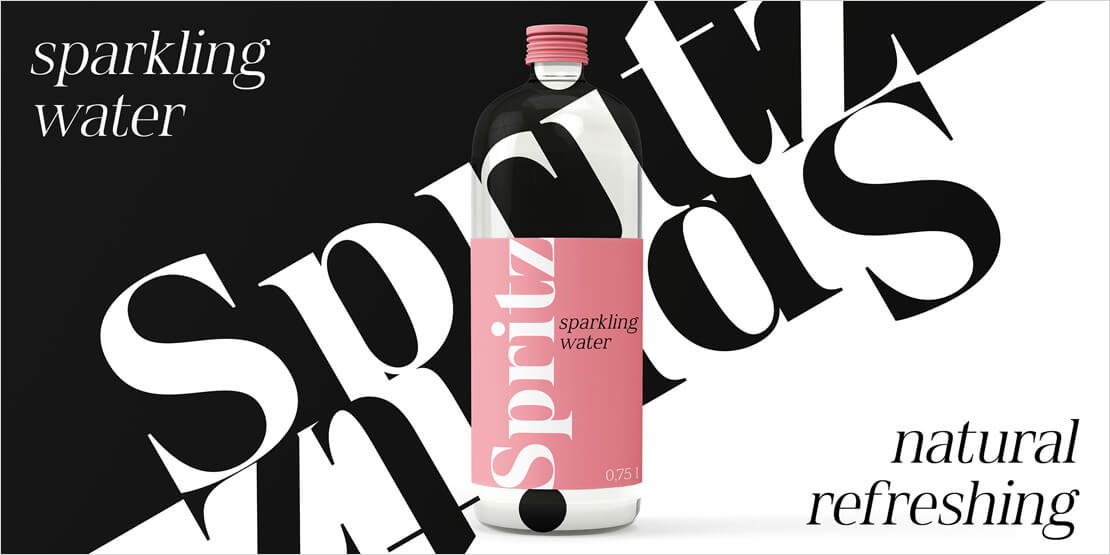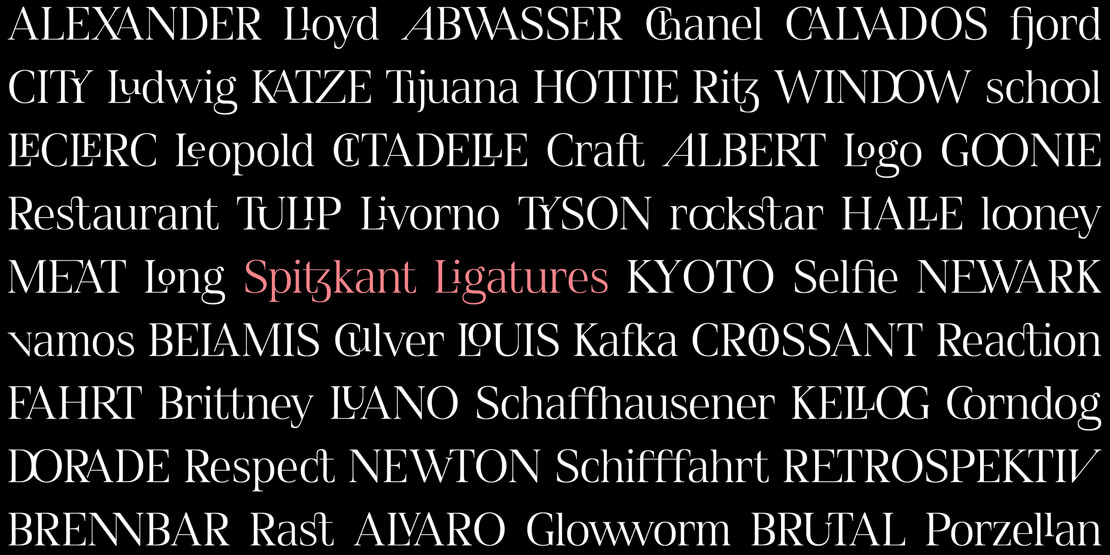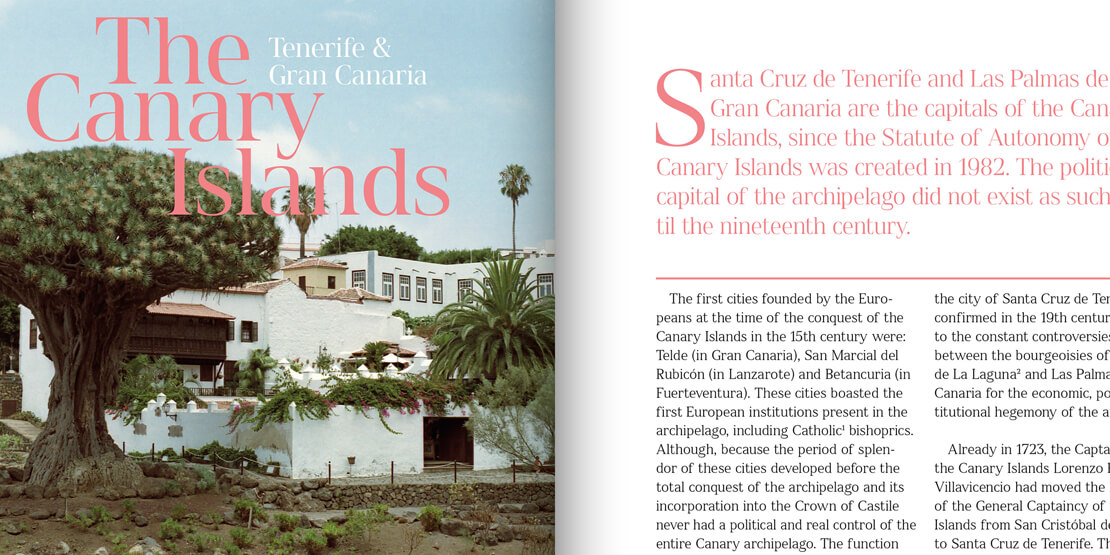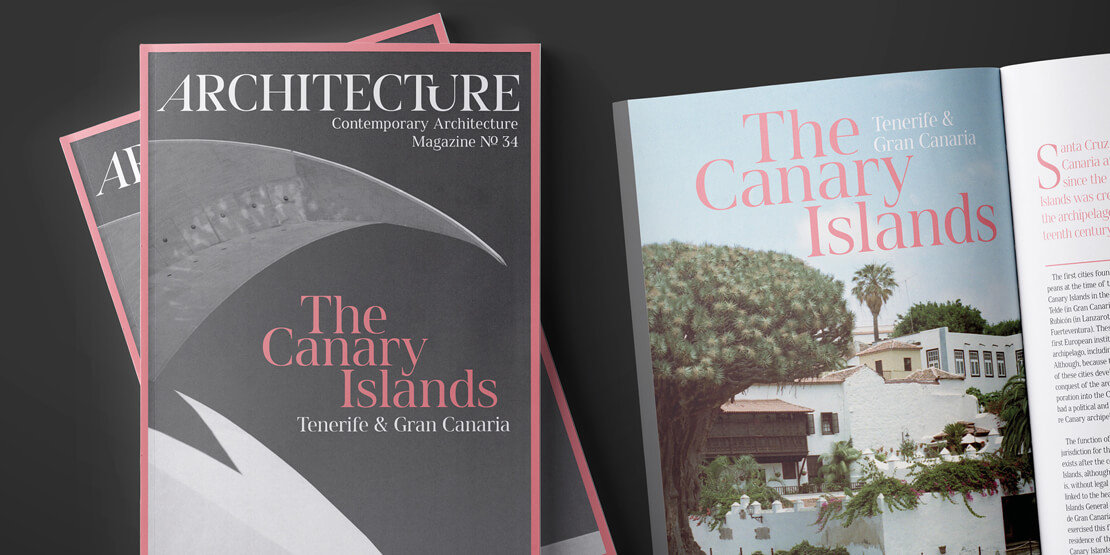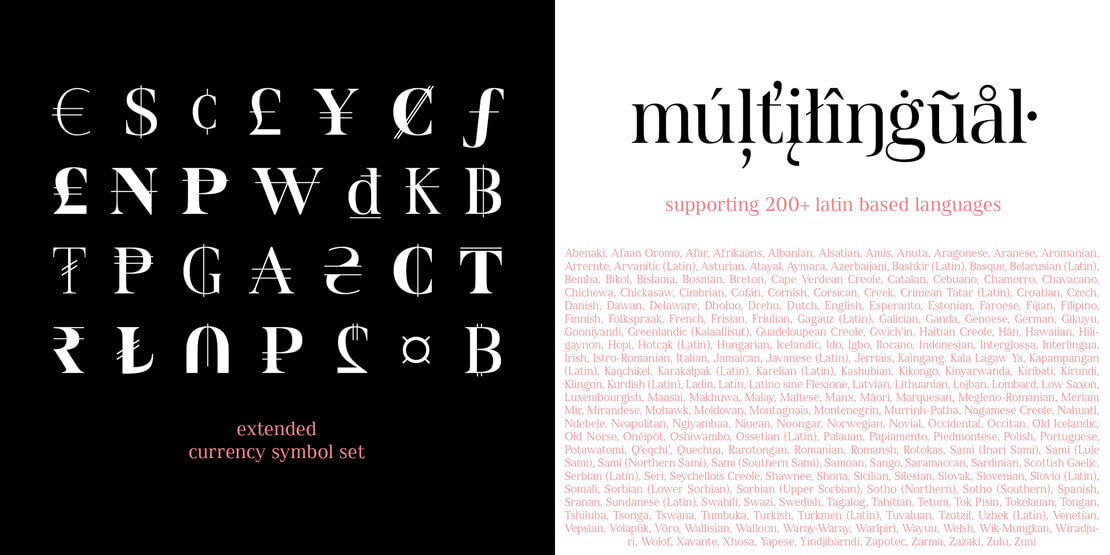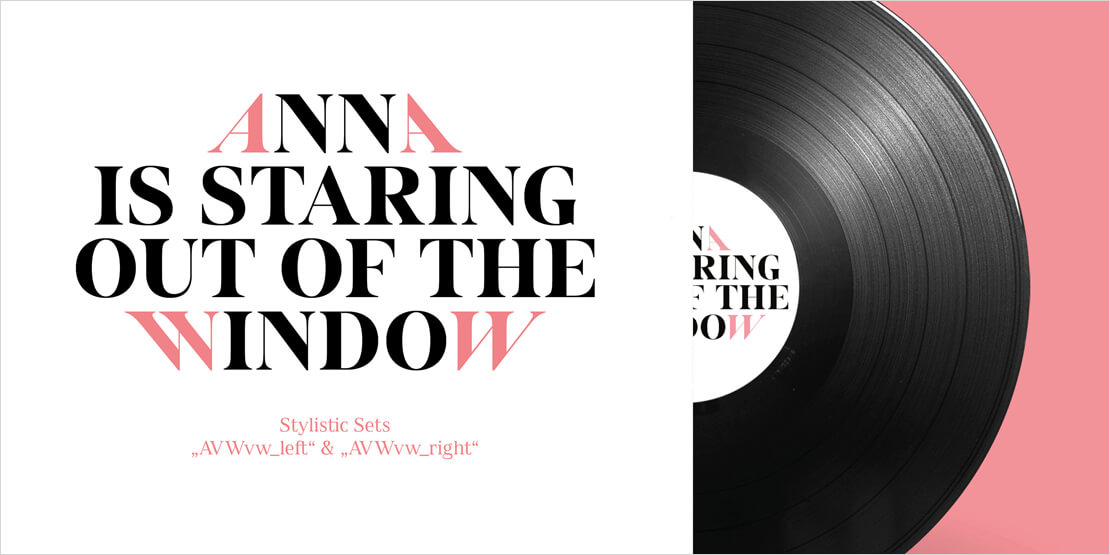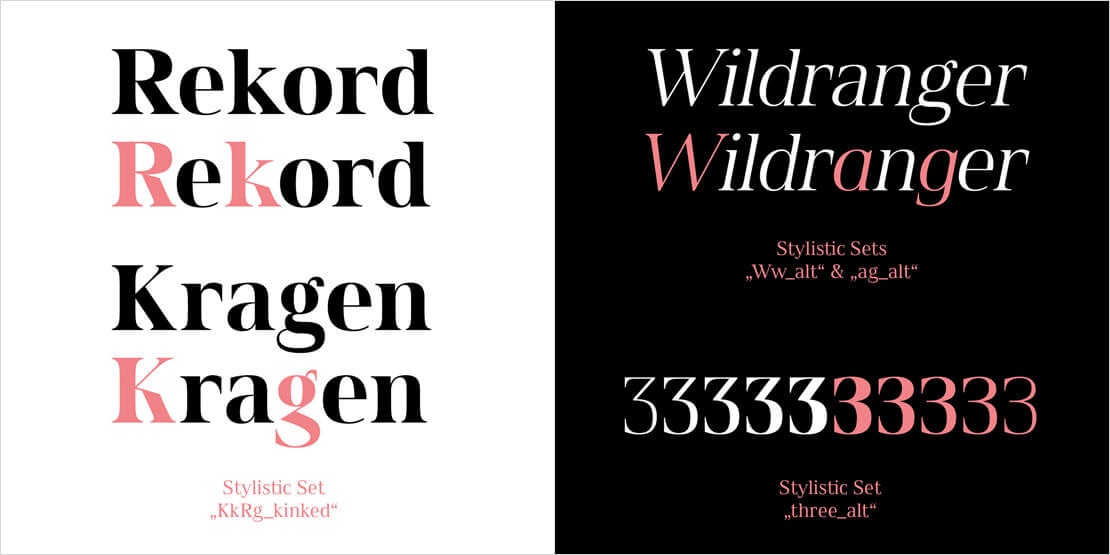
Schriftfamilie »Spitzkant« von Julien Fincker erschienen
»Spitzkant« ist eine Serifenschrift, konzipiert sowohl für Headlines und Displaygrößen, als auch für umfangreiche Fließtexte. Spitze, scharfkantige Serifen und Kanten stehen runden und feinen Formen gegenüber.
Über die Schriftfamilie »Spitzkant«
Die Head- und Text-Familie von Spitzkant verfügt über insgesamt 2 optische Größen, 5 Gewichte und 20 Schnitte, von »Thin« bis »Bold« sowie passenden kursiven Schnitten.
Mit über 850 Zeichen deckt sie über 200 lateinbasierte Sprachen ab. Sie verfügt dabei über eine Vielzahl an Währungszeichen und Open Type Features. Es gibt beispielswiese alternative Zeichen als Stylistic Sets, Small Caps, automatische Brüche und weitere Features.
Der kontrastreichen Display-Variante wurde eine kontrastärmere Text-Variante beigestellt, sodass Spitzkant in Kombination sowohl für starke Headlines als auch für umfangreiche Fließtexte geeignet ist. Mit über 95 verschiedenen Ligaturen bieten sich viele Möglichkeiten, Headlines und Logos eine individuelle Note zu geben.
Der Designprozess der »Spitzkant«
Nachdem Julien Fincker etwa ein Jahr mit der Gestaltung der beiden Schriftfamilien Finador Sans und Finador Slab verbracht hatte, benötigte der Designer für seine nächste Schrift ein absolutes Kontrastprogramm zu den runden und gleichmäßigen Formen.
Nach ein paar ersten Skizzen stand der Plan fest: Spitz, kantig und mit starken Kontrasten in der Linienführung sollte es sein.
»Bereits in der Konzeptionsphase skizzierte ich die ersten Ligaturen. Von Beginn an legte ich großen Wert auf den Ausbau einer umfangreiche Ligaturen-Sammlung.«, so der Designer. »Sie bietet viele Möglichkeiten, um sehr individuelle Headlines formen zu können. Für mich, gerade auch als Grafikdesigner, eines der wichtigsten Features um mit der Schrift Neues entdecken und sich richtig austoben zu können.«
Ursprünglich war »Spitzkant« als reine Display-Schrift gedacht. Als etwas »Schnelles« nach den umfangreichen Finador-Familien. Jedoch sah der erste Ausdruck in kleinen Größen eher vielversprechend aus. Daher entschloss sich der Kreative, dem noch eine kontrastärmere Text-Version hinzuzusetzen. »Und wenn man schon den Extrameter läuft, läuft man noch zwei mehr. Also wurden viele weitere Sprachen und Features ergänzt. Somit ist Spitzkant eine inhaltlich sehr abgerundete und umfangreiche Familie geworden, die sich für viele Zwecke nutzen lässt. Extrameter die sich definitiv gelohnt haben.«, so Julien Fincker.